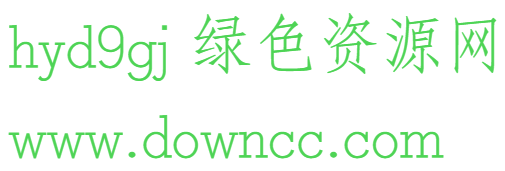
hyd9gj字體
hyd9gj 0325字體是一款結(jié)構(gòu)錯落有序的漢儀仿宋字體,筆畫清晰字形干凈,適合排版印刷、報刊正文、包裝設計等方面或是用作廣告字體也可以,有需要者快來綠色資源網(wǎng)下載吧!
仿宋字體介紹
仿宋是印刷字體的一種,仿照宋版書上所刻的字體,筆畫粗細均勻,有長、方、扁三體,也叫仿宋體,仿宋字。仿宋體是仿照宋版書的字體演變而來的,但仿宋的結(jié)構(gòu)特征決定了它必須有一定的傾斜。
仿宋體優(yōu)點
仿宋是主要的中文字體之一,但是它的使用頻率并沒有宋體、楷體高,而其實我們在電腦上面看到的仿宋是字體設計者根據(jù)古籍作品加工的,刪去了一些細節(jié),使得字體更加平滑,但是卻失去了一些字體原型的風韻。